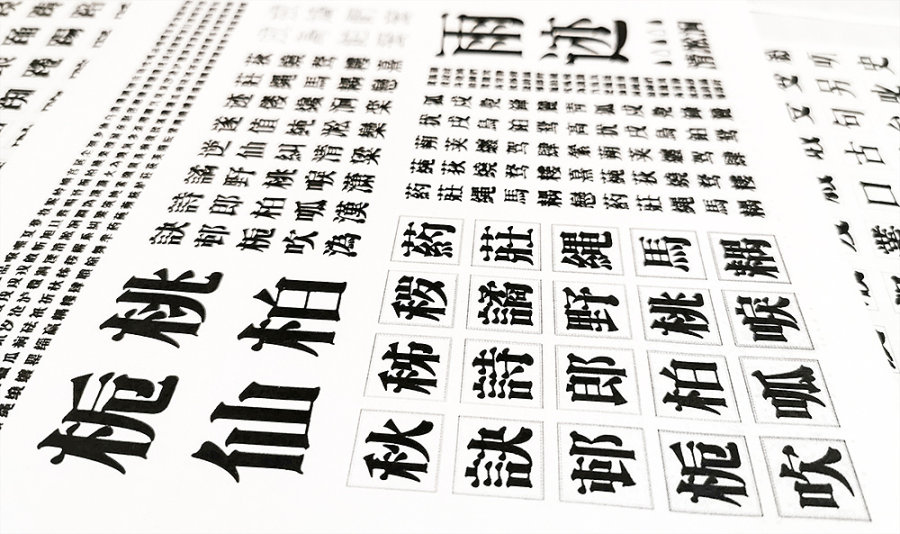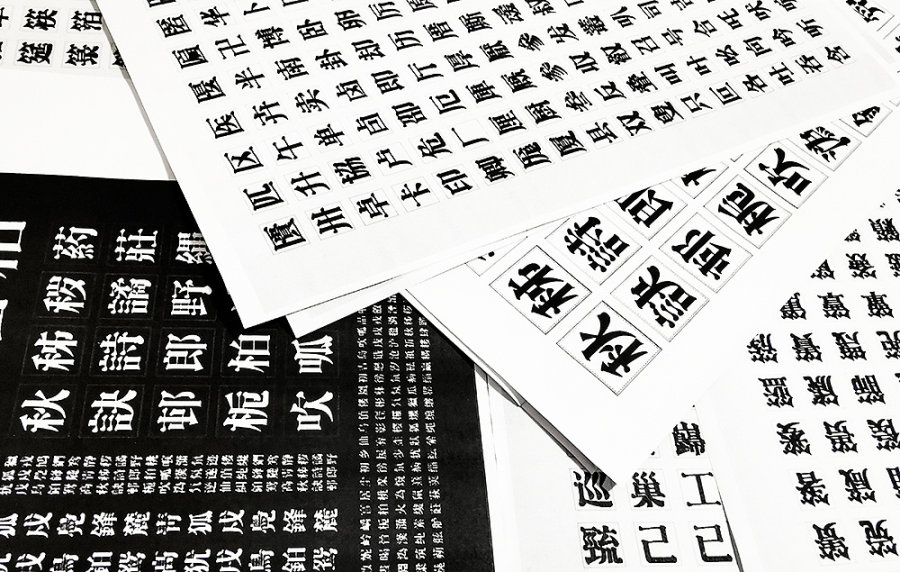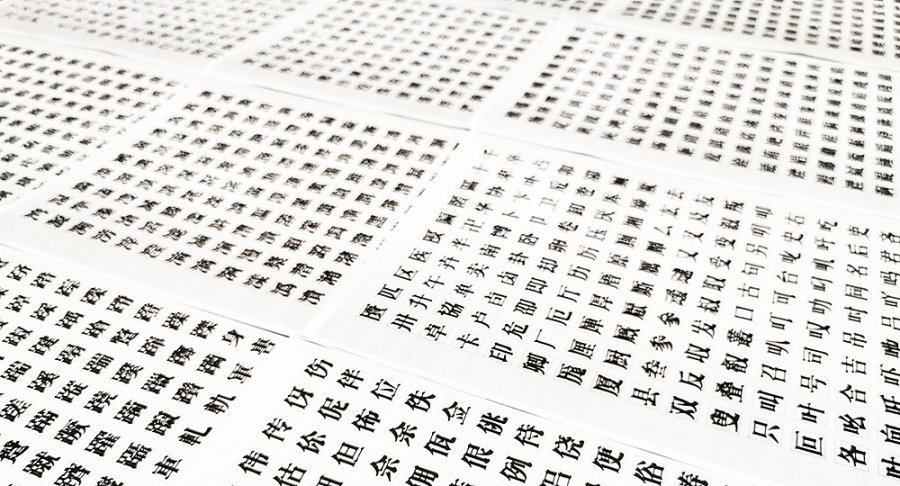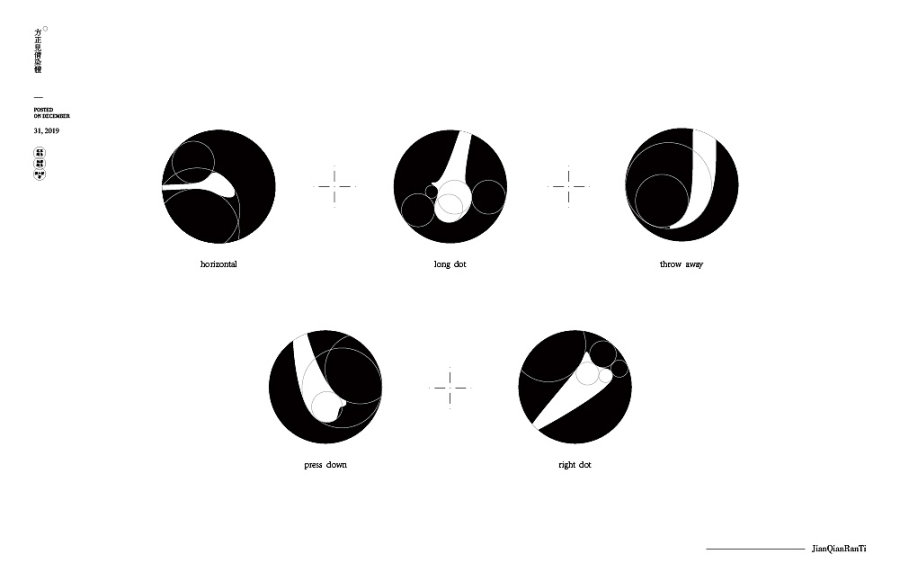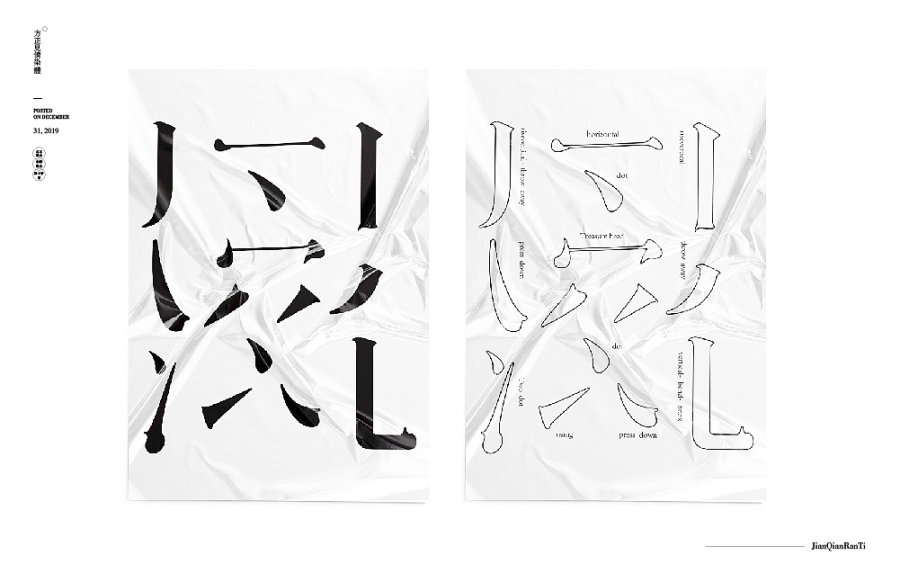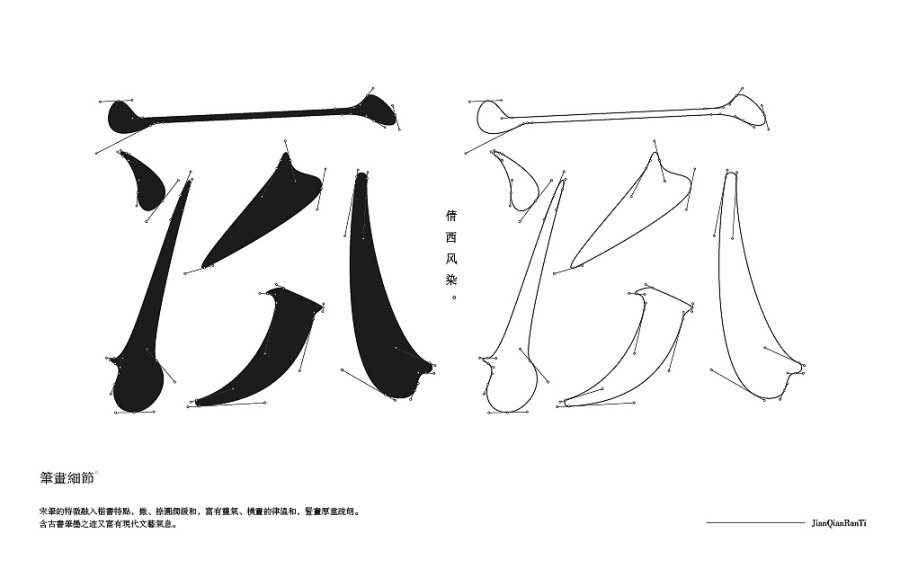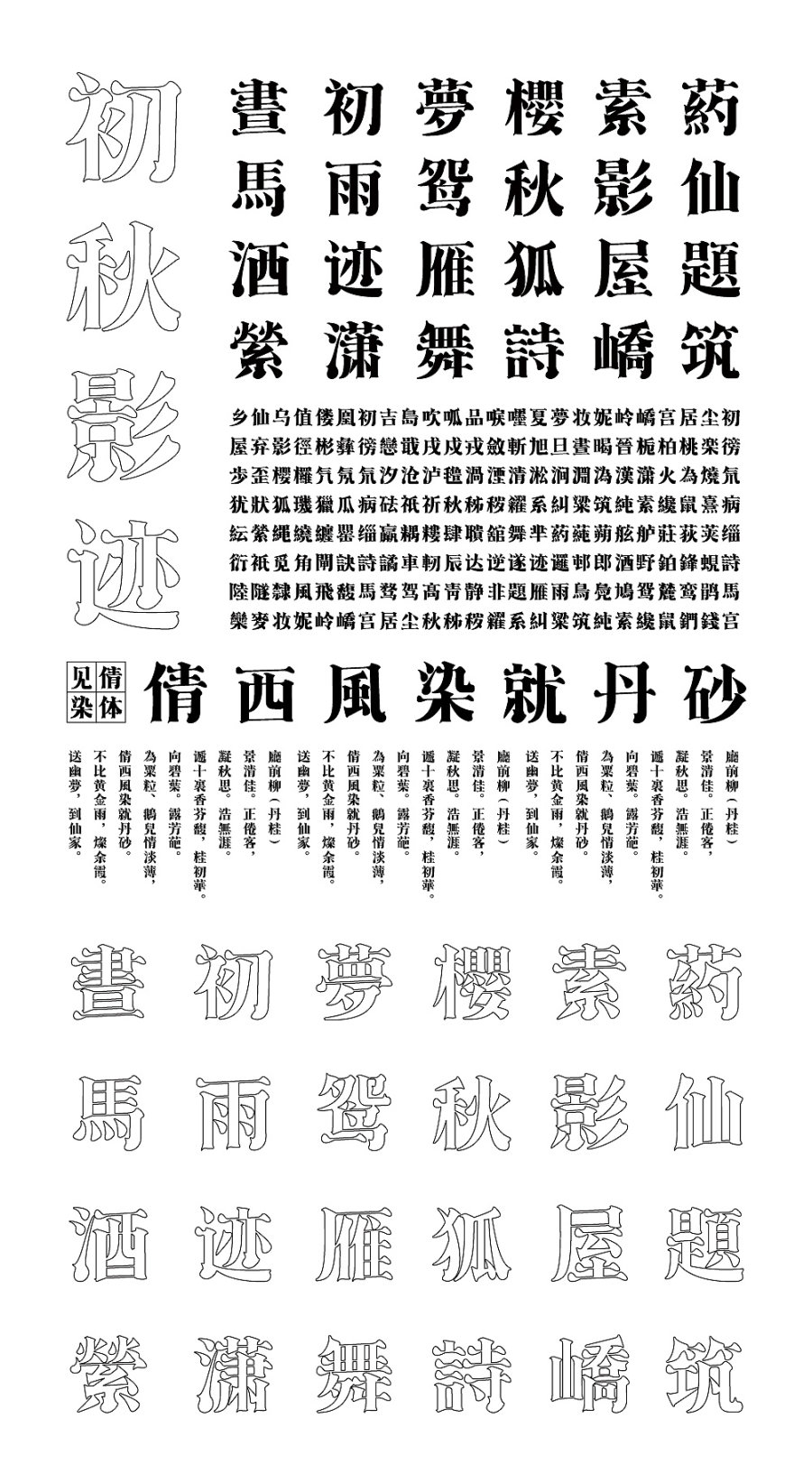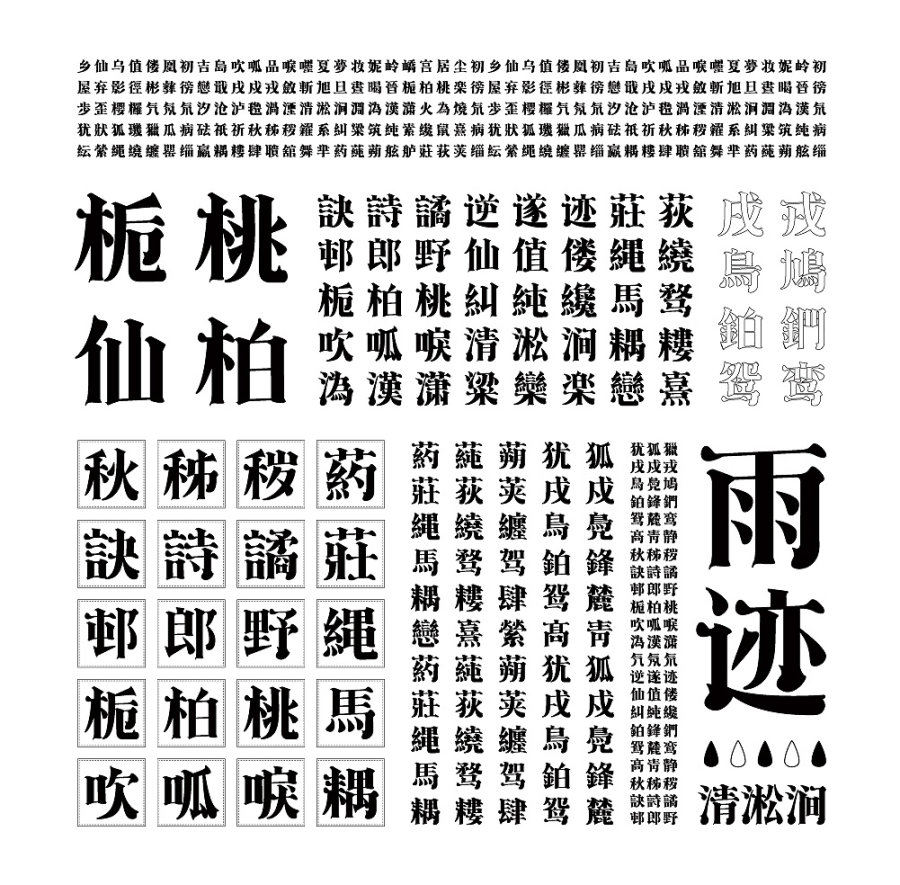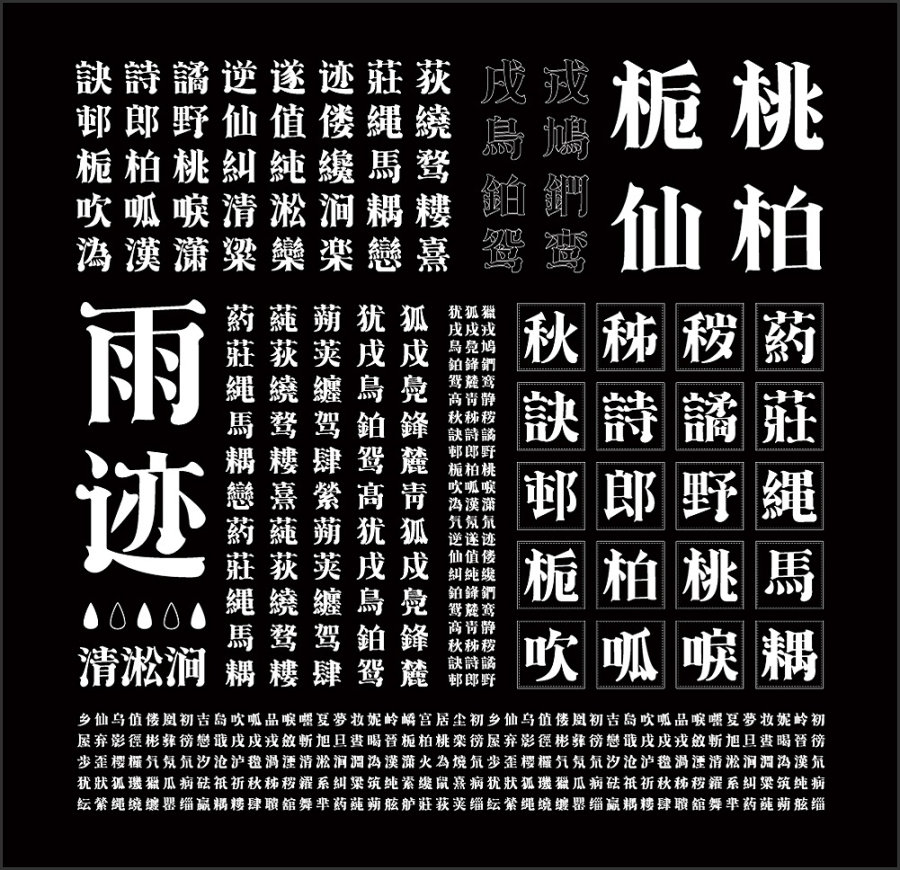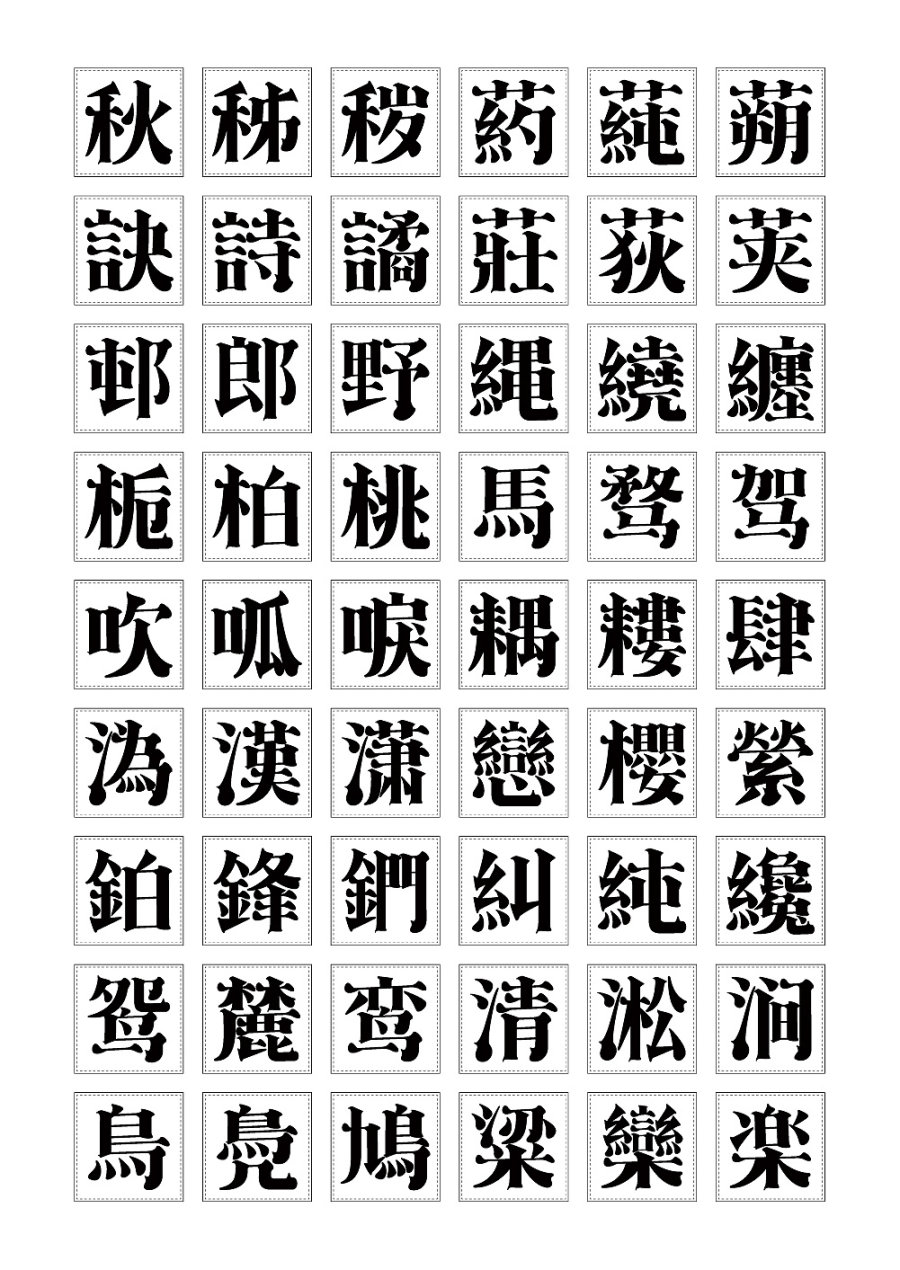
2020新字首发
方正见倩染体
字形以宋体为原型演变,融入楷书特征,整体均匀平稳,清和雅致。
横画韵律温和,竖画厚重疏朗,蕴含古书笔墨之迹又富有现代文艺气息。
简繁扩展(GBK),共计9660余字
适用于商业广告、标题、产品包装、品牌名、文化类印刷等。
2018年3月开始独立创作,同年8月完成。
字体设计:陈小发